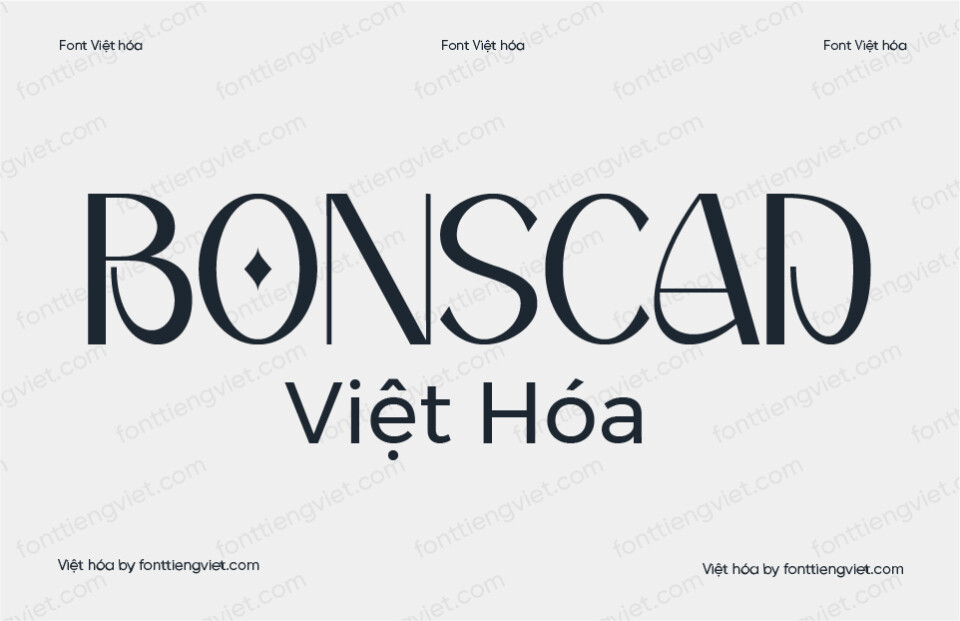
Font Việt hóa 1FTV VIP Bonsad
Giới thiệu về Font Việt hóa 1FTV VIP Bonsad
Trong thế giới sáng tạo, việc lựa chọn một Font Miễn Phí chất lượng là yếu tố then chốt để tạo nên sự khác biệt. Font Việt hóa 1FTV VIP Bonsad nổi bật như một giải pháp thiết kế chuyên nghiệp, mang đến vẻ đẹp hiện đại và tinh tế cho mọi dự án. Được tinh chỉnh kỹ lưỡng về dấu tiếng Việt, bộ font này giúp người dùng dễ dàng trình bày nội dung mà không lo lỗi hiển thị. Đây là lựa chọn lý tưởng cho các bạn học sinh và giáo viên khi soạn thảo giáo án hay làm slide thuyết trình sinh động.
Đặc điểm nổi bật của Font Việt hóa 1FTV VIP Bonsad
Phong cách thiết kế độc đáo
Bộ Font Việt hóa 1FTV VIP Bonsad sở hữu đường nét thanh thoát, cân đối giữa các nét thanh và nét đậm. Điều này tạo nên cảm giác dễ chịu cho mắt người đọc, giúp thông tin được truyền tải mạch lạc hơn. Với khả năng tương thích cao trên nhiều phần mềm thiết kế như Photoshop hay Canva, bạn có thể thỏa sức sáng tạo các mẫu poster, thiệp mời hoặc bìa sách giáo khoa đầy ấn tượng.
Tối ưu hóa cho người dùng Việt
Điểm mạnh nhất của bộ font này chính là sự tỉ mỉ trong khâu Việt hóa. Các ký tự đặc trưng của tiếng Việt được thiết kế hài hòa, không gây cảm giác lệch lạc so với bảng chữ cái gốc. Sự ổn định này giúp quy trình làm việc trở nên nhanh chóng và hiệu quả hơn bao giờ hết.
Kết luận và trải nghiệm Font Việt hóa 1FTV VIP Bonsad